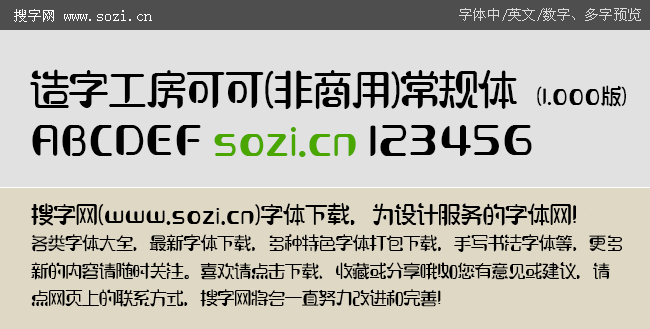
造字工房可可(非商用)常規(guī)體
搜字網(wǎng)提供一款造字工房可可(非商用)常規(guī)體中文字體下載,造字工房可可體筆畫上做了大膽的嘗試創(chuàng)新,在保持整體風(fēng)格中大膽變幻、勢合形離。筆畫渾圓淳和 、內(nèi)蓄勁力?诓糠止P畫的斷開更加凸顯字體的風(fēng)格特點。點線面的穿插、像一首有節(jié)奏的樂章、起承轉(zhuǎn)合恰到好處,活潑而飽滿。此款字體適用于主副標(biāo)題及個性品牌的設(shè)計等應(yīng)用。